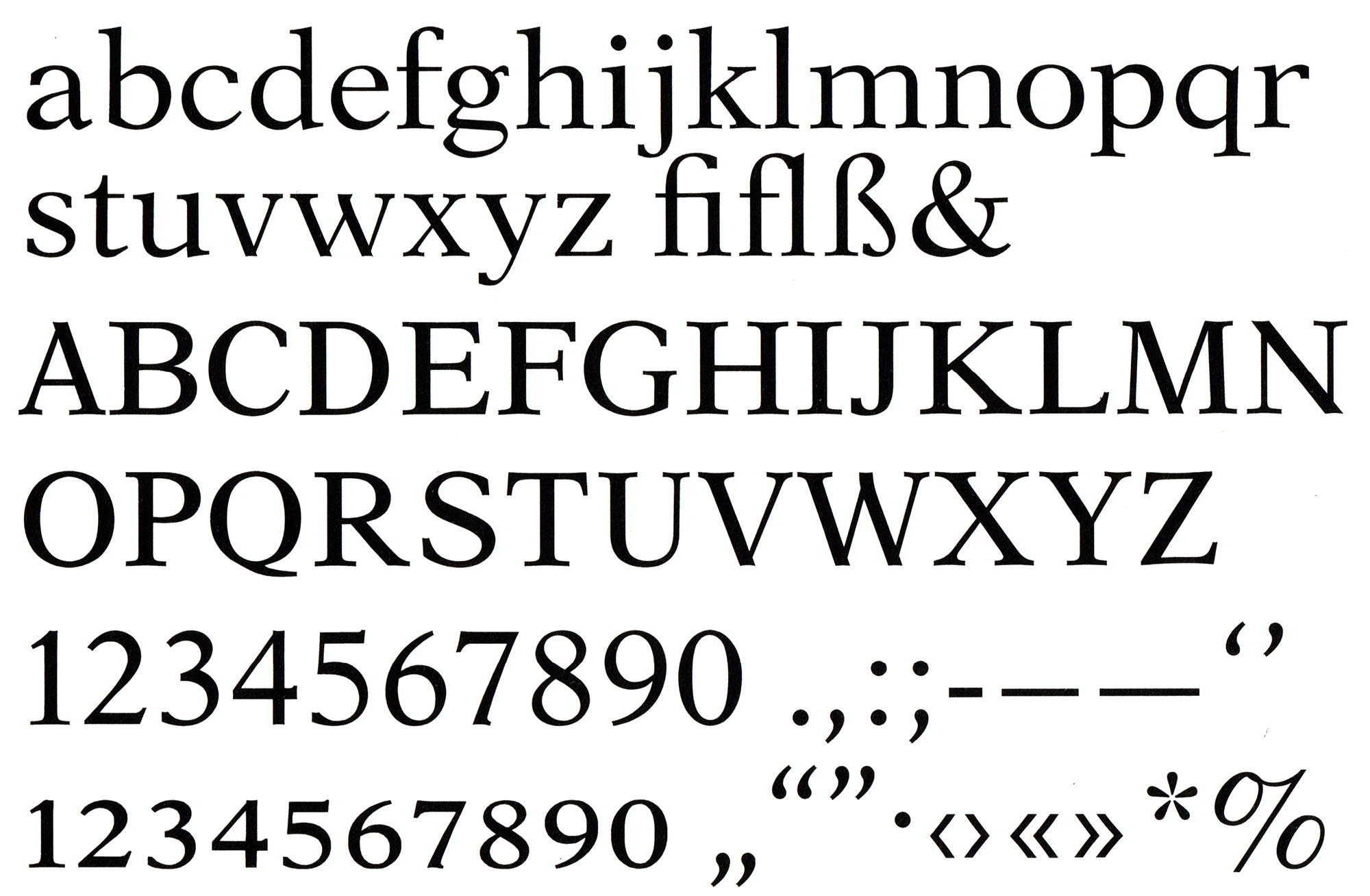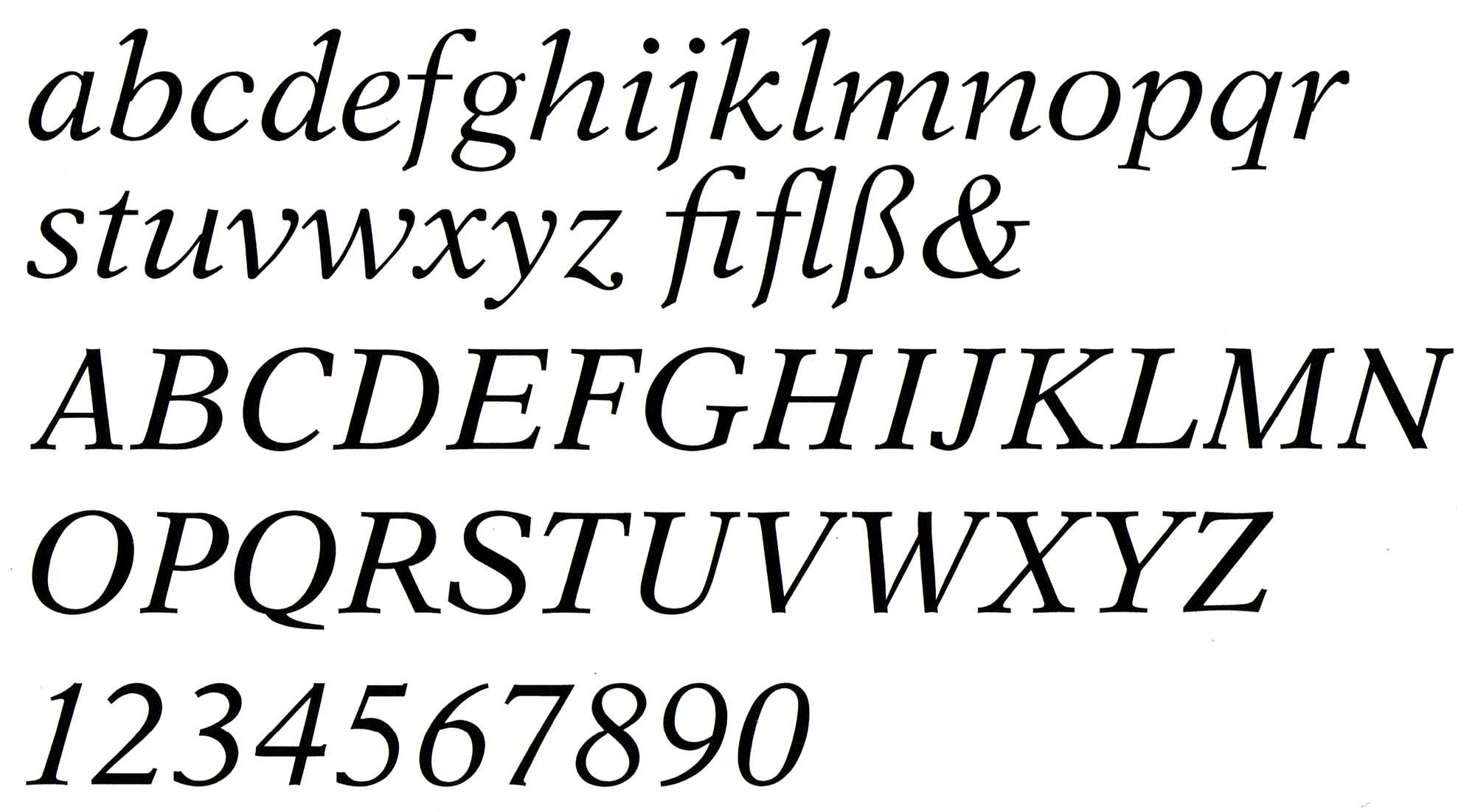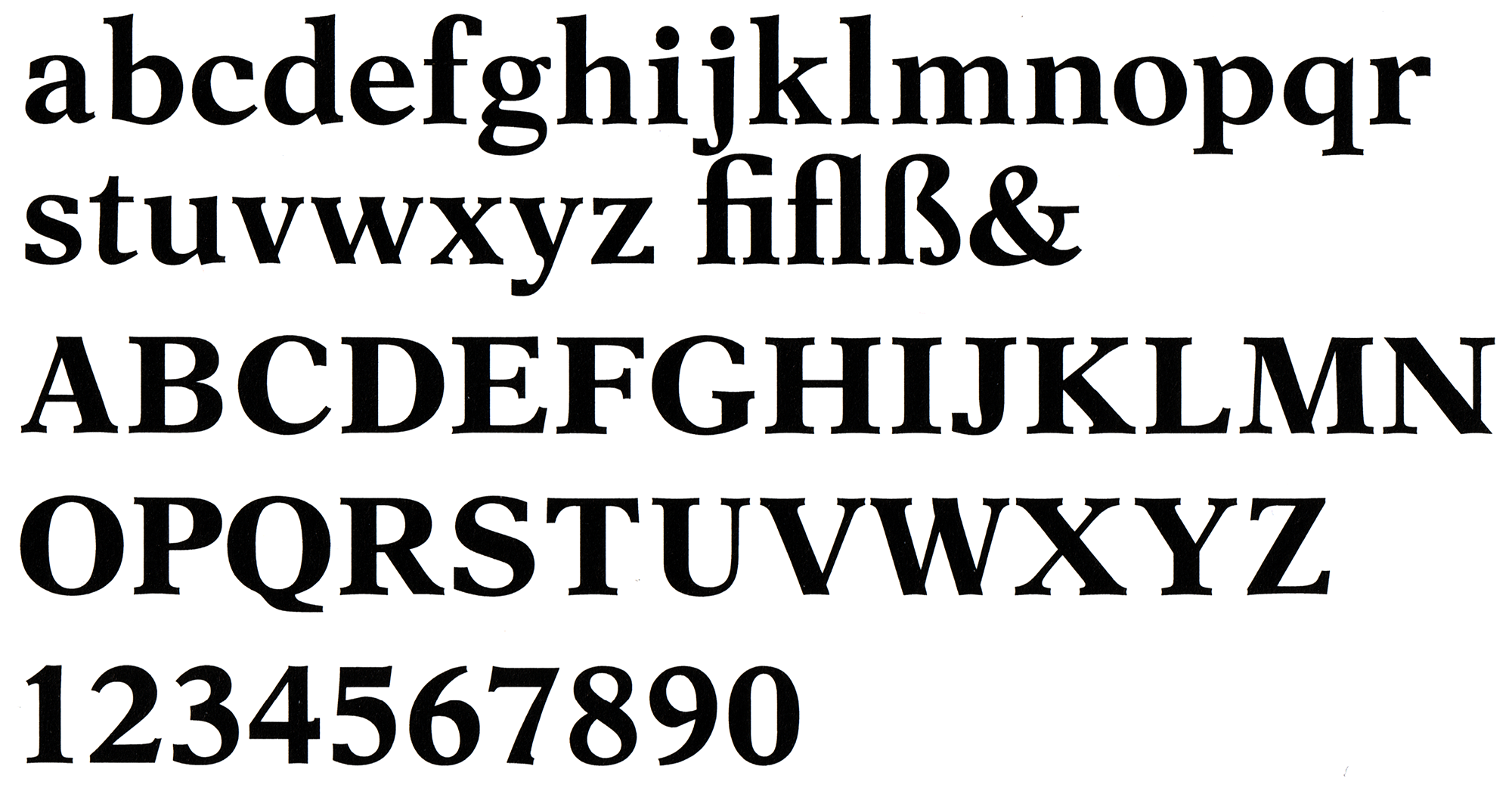
• 1958
• Serifen:
• serif
• Antiqua humanistisch
Die Aster ist eine Antiqua-Familie von Francesco Simoncini aus den 1950er-Jahren. Die Schrift war auf Fließtextanwendungen ausgelegt und kam entsprechend in den Schnitten normal, kursiv und fett.
In den 1980er-Jahren wurde die Schrift für den Fotosatz neu aufgelegt und erweitert. Die New Aster verfügte über vier Strichstärken mit Kursiven. Diese Schnitte sind heute auch digital über Linotype verfügbar.